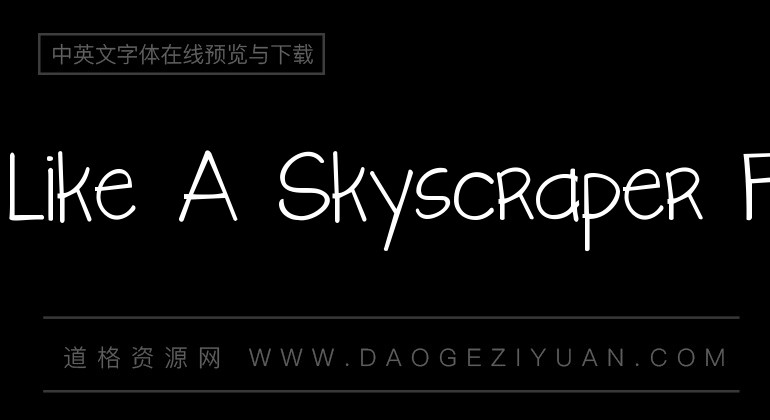
KG Like A Skyscraper是一种免费的手写字体,由Kimberly Geswein设计。它是一种非常有趣和现代的字体,具有类似于手写笔划的外观,字母的形状比较简单,但是它们的大小和间距使得字体看起来非常适合于设计海报、宣传册和印刷品。 这种字体的特点是它的笔画不太规则,并且字母具有不同的大小和形状。它还包括许多附加的装饰符号和符号,这些符号的风格与字体相匹配。 KG Like A Skyscraper适用于许多不同的设计项目,包括海报、邀请函、贺卡、广告和徽标。这种字体的设计带有一种现代和有趣的感觉,它可以使您的设计看起来更加个性化和专业化。内容介绍
KG Like A Skyscraper Font是一款非常不错的手写艺术字体,具有很好的视觉感,适合于文化类的宣传设计、商业类品牌的广告和产品包装设计以及个性化文字排版等较多场景。